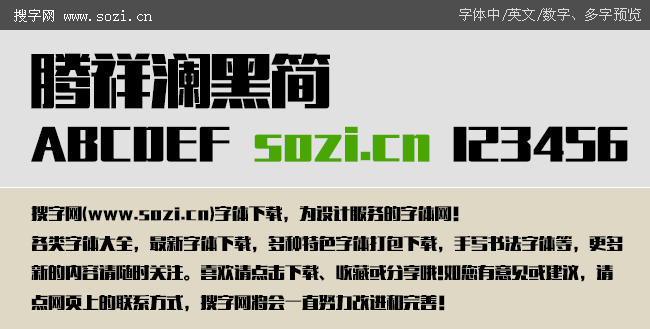
騰祥瀾黑簡(jiǎn)
搜字網(wǎng)提供一款騰祥瀾黑簡(jiǎn)中文藝術(shù)字體下載,騰祥瀾黑整體字形筆畫均衡,風(fēng)格現(xiàn)代,風(fēng)格清晰端正,適合標(biāo)題用字,可用于印刷出版、包裝設(shè)計(jì)、廣告設(shè)計(jì)、網(wǎng)頁(yè)設(shè)計(jì)等。